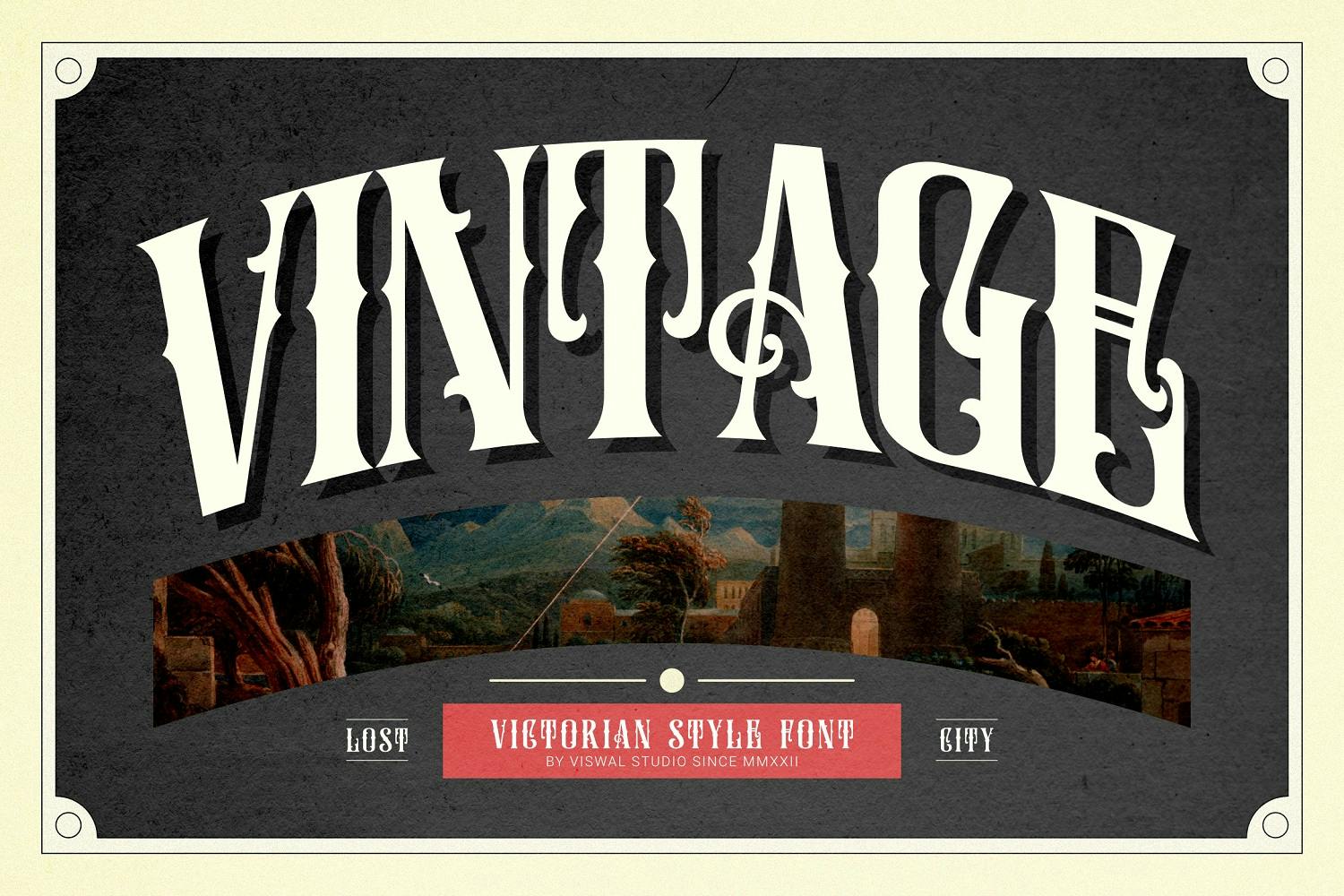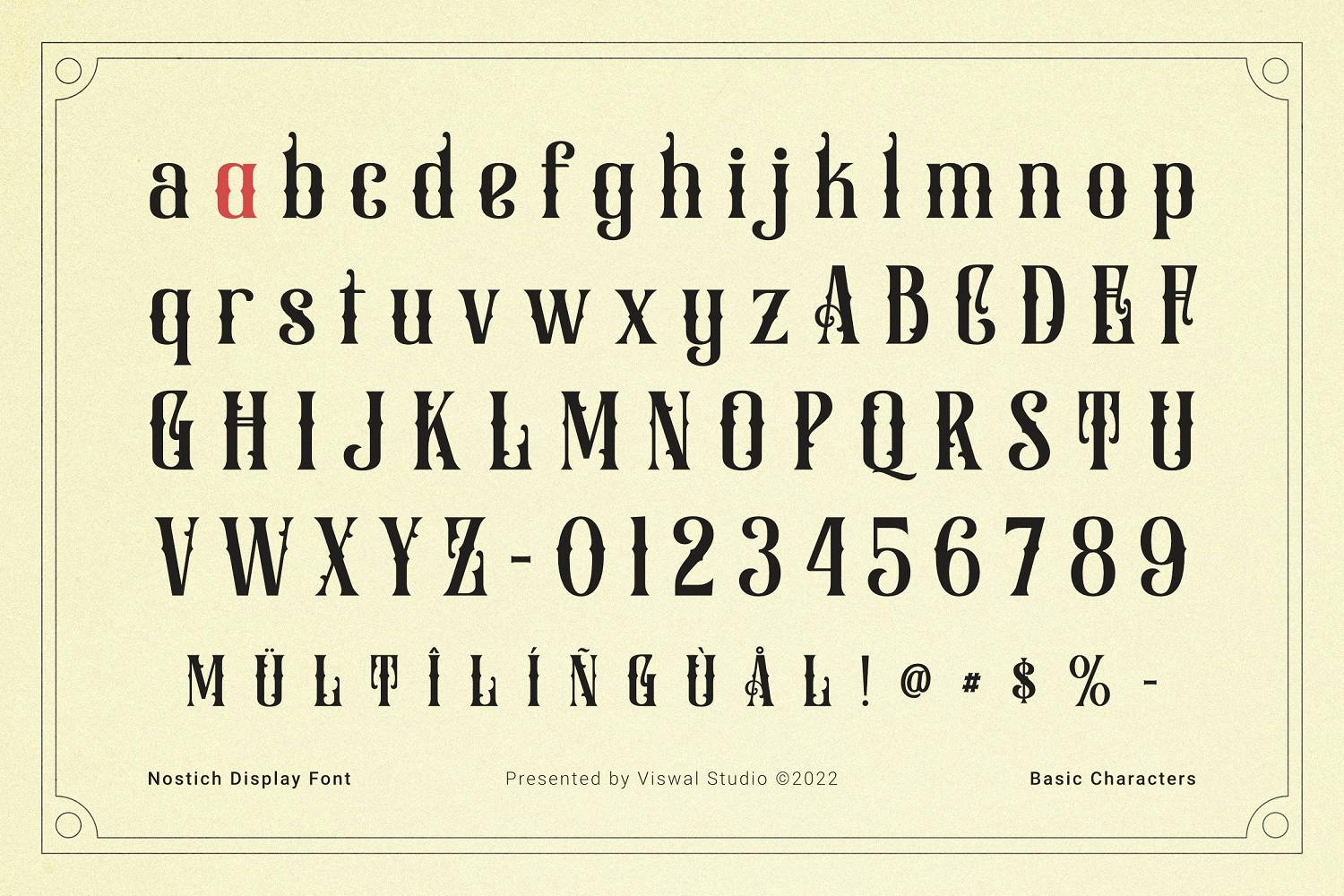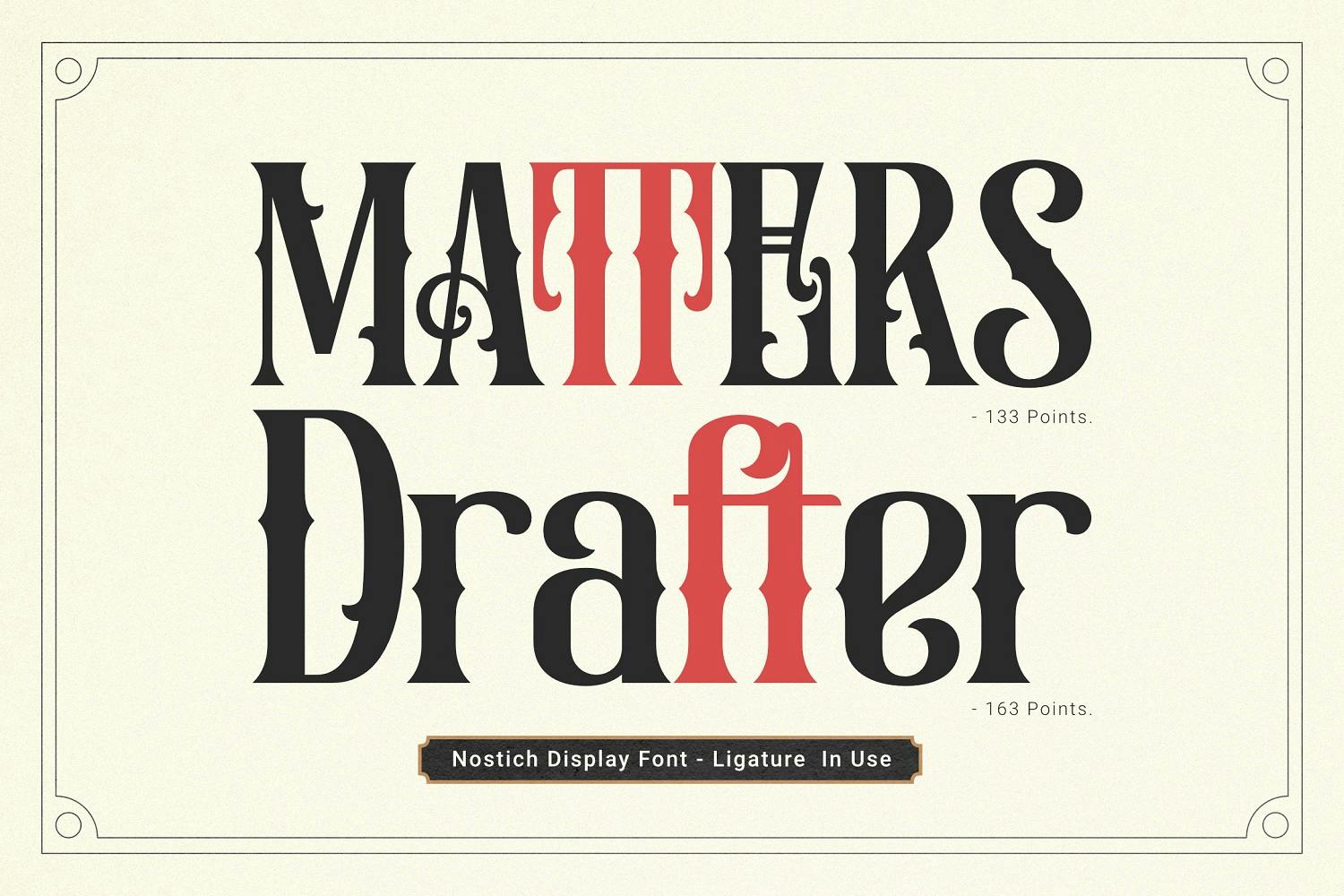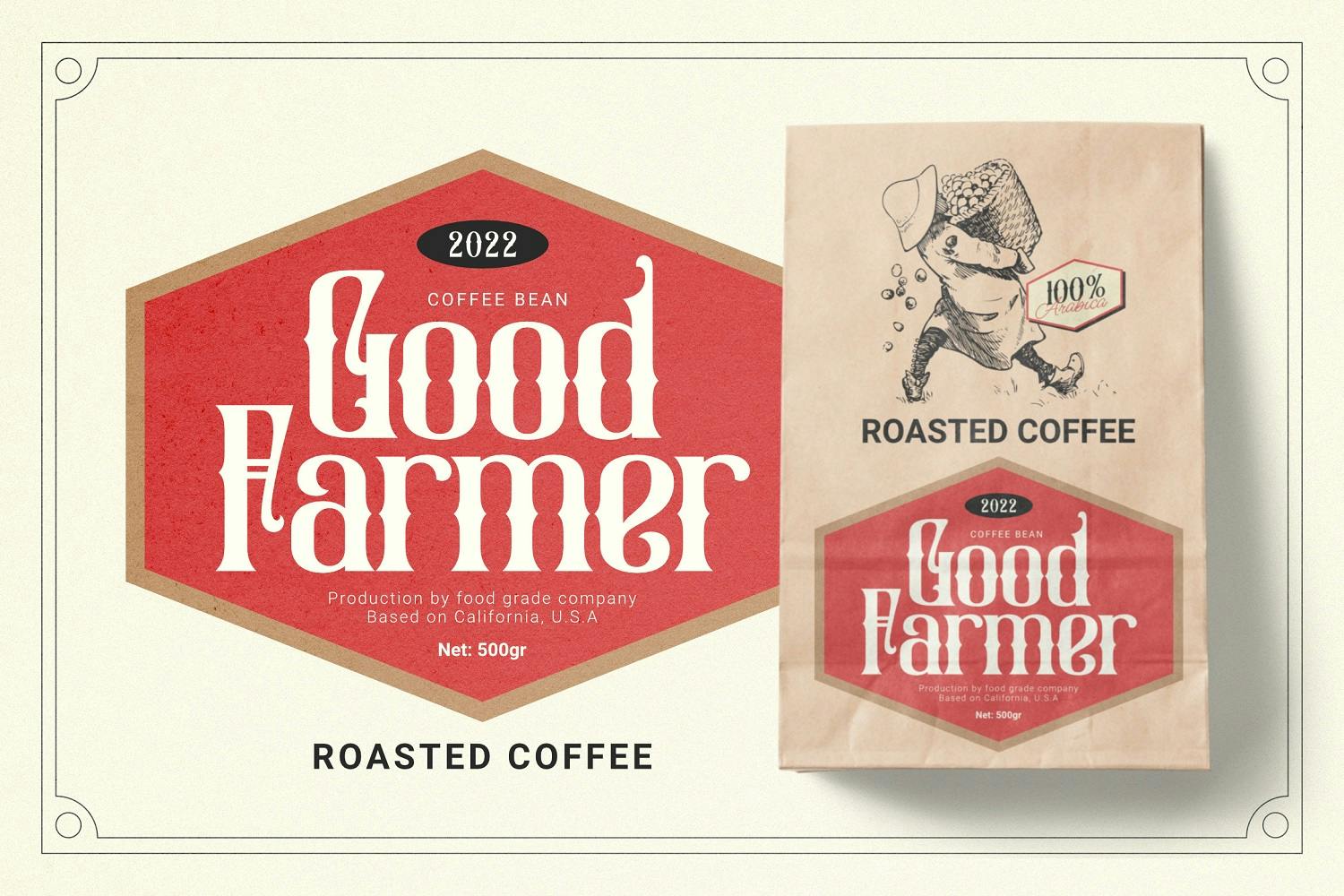
فونت Nostich - وینتیج، گزینهای عالی برای طراحی برچسب، لوگو، برندینگ، مجله، پوستر و موارد دیگر است. این فونت شامل حروف بزرگ و کوچک، اعداد و نشانهگذاری، پشتیبانی چندزبانه و ویژگیهای OpenType میباشد. برای طراحیهای شگفتانگیز، میتوانید آن را با سایر فونتها ترکیب کنید تا جلوهای خاص به پروژههای خود ببخشید.